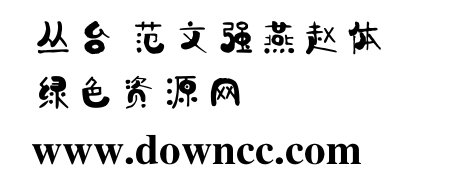
叢臺(tái) 范文強(qiáng)燕趙體
范文強(qiáng)燕趙體是叢臺(tái)字庫(kù)推出的一款獨(dú)具燕趙地區(qū)特色的古風(fēng)毛筆字體,造型設(shè)計(jì)上非常有個(gè)性,每個(gè)漢字都蘊(yùn)含著濃烈的古風(fēng)氣息,感興趣的小伙伴就來(lái)綠色資源網(wǎng)試試吧!
叢臺(tái) 范文強(qiáng)燕趙體作者介紹
范文強(qiáng),男,1980年出生,邯鄲市叢臺(tái)區(qū)五里鋪人,自幼喜愛(ài)書(shū)法,燕趙體發(fā)明者。
懷著對(duì)燕趙文化的特殊感情,開(kāi)始走街串巷,看到有文化的東西就把它記下來(lái),在研習(xí)創(chuàng)作中推陳出新。受趙國(guó)和氏璧以及燕趙錢(qián)幣、古兵器等啟發(fā),范文強(qiáng)開(kāi)始研發(fā)創(chuàng)作“燕趙體”。
燕趙體
該字體共錄入6763個(gè)常用漢字,符合國(guó)家區(qū)位編碼GB2312—1980標(biāo)準(zhǔn),廣大網(wǎng)民可以免費(fèi)下載、安裝和使用。
字體設(shè)計(jì)理念
自幼愛(ài)好燕趙文化、書(shū)畫(huà),懷著對(duì)燕趙文化的特殊感情,從2014年開(kāi)始,范文強(qiáng)開(kāi)始走街串巷,看到有文化的東西,就把它記下來(lái),在研習(xí)創(chuàng)作中推陳出新,尊古而不循古,不斷在繼承之中求新、求變,在個(gè)性化的創(chuàng)作中賦予作品以時(shí)代精神和文化特質(zhì),真正做到臨摹改變、大膽創(chuàng)新。2016年初,《范文強(qiáng)燕趙體》面世了,該字體融入了燕趙文化元素符號(hào),結(jié)合趙國(guó)和氏璧以及燕趙錢(qián)幣、古兵器等造型,最終形成軟曲而柔、豐厚而腴、纖細(xì)而秀,起筆有方圓尖和藏露變化的字體。